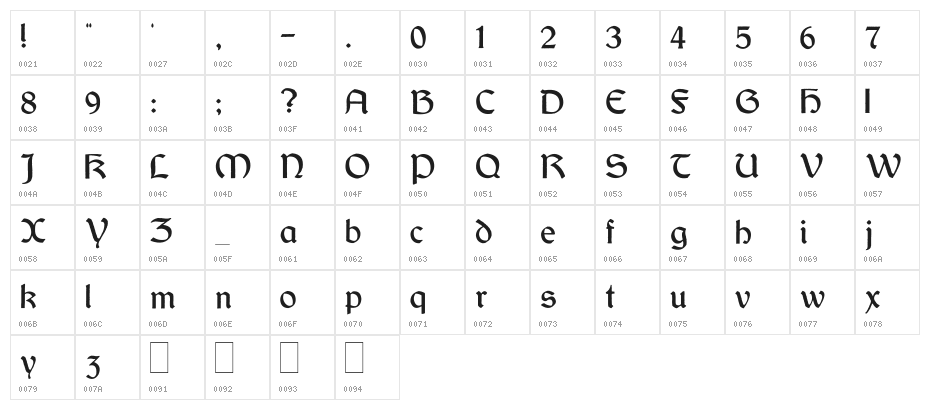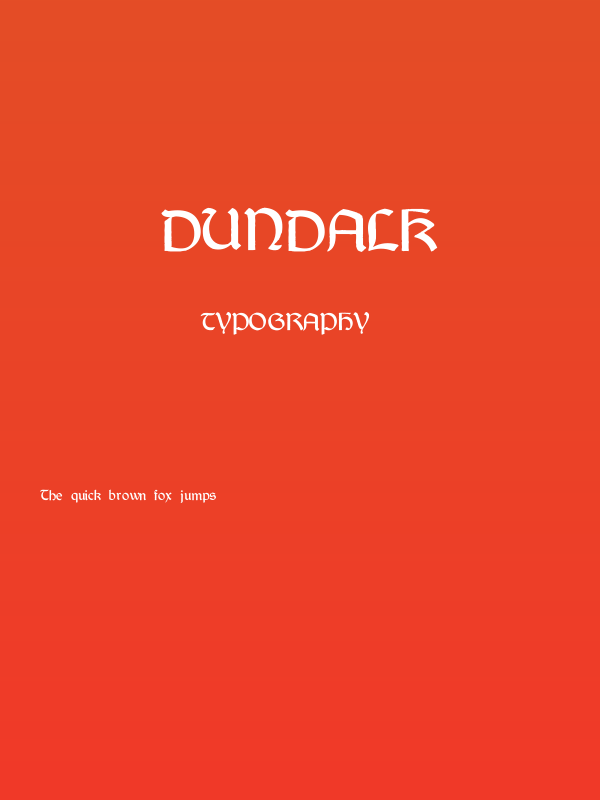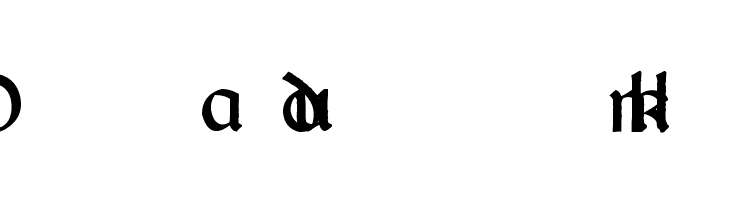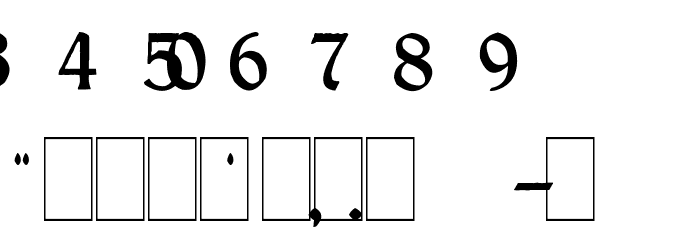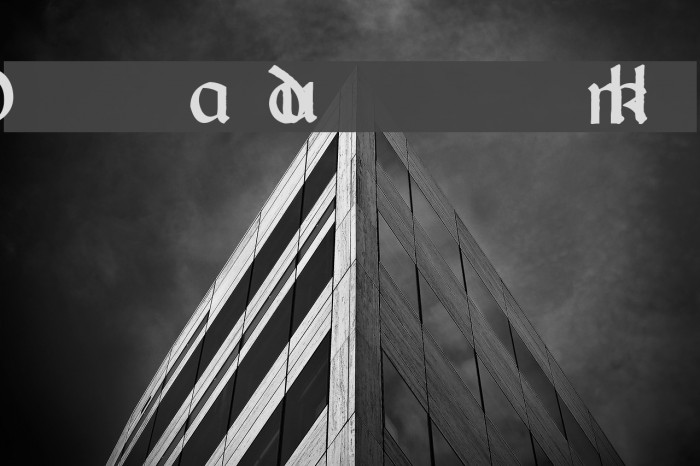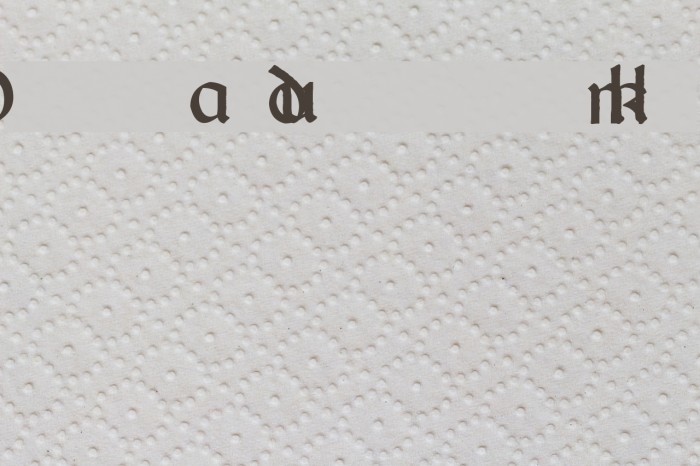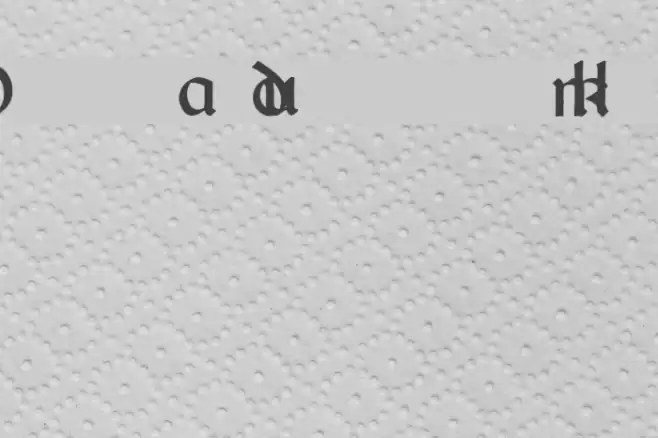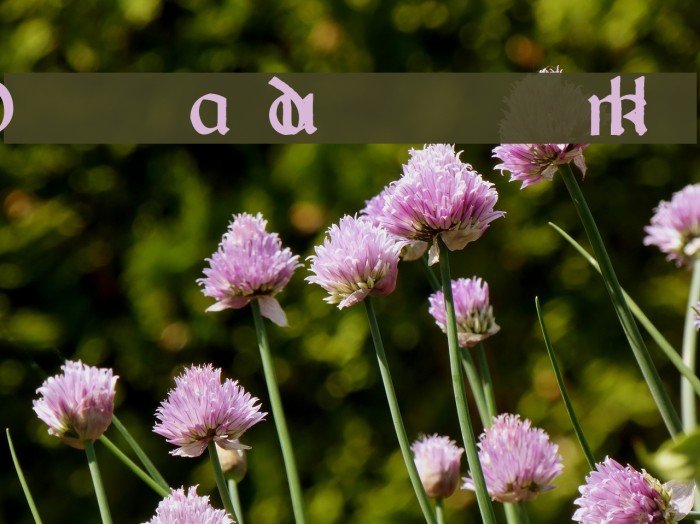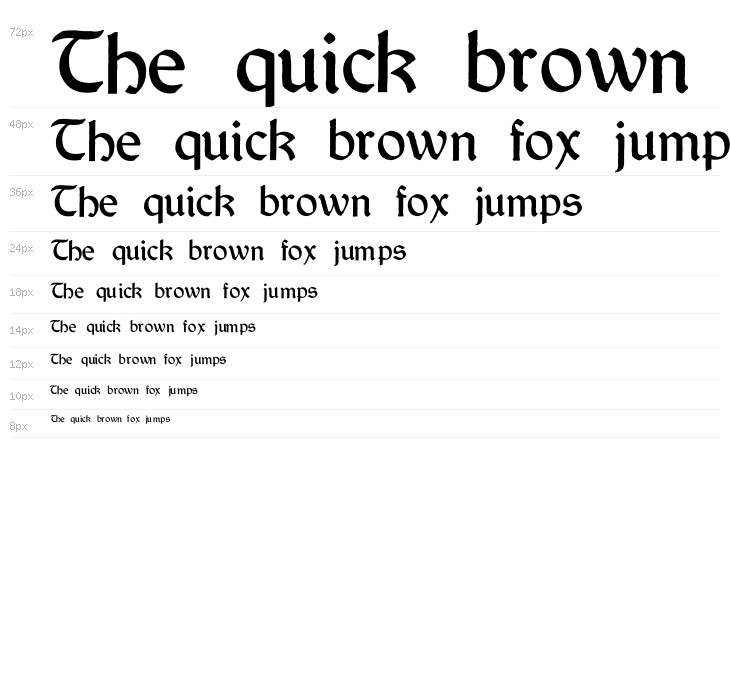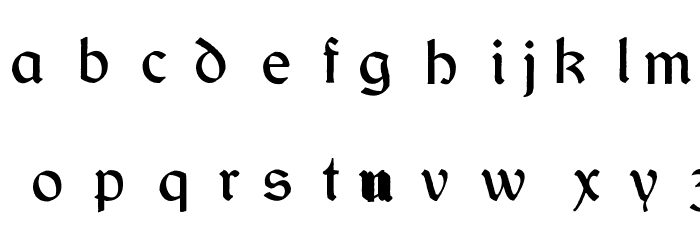
Dundalk Font
| Cas d'utilisation | Logos, Headlines, Decorative text |
| Projets proposés | Ideal for historical documents, vintage posters, book covers, or any design needing a medieval or Gothic theme. |